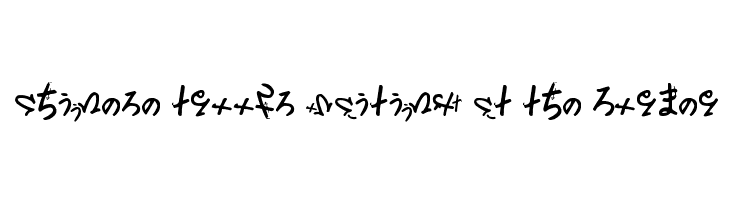
A dynamic and flowing script font with elegant cursive letterforms.
A jagged, hand-drawn font with a gothic, artistic style.
A modern, geometric sans-serif font with clean lines and a technical look.
A bold, decorative font with a 3D effect and dotted textures.
A bold, playful font with rounded strokes and a whimsical style.
A modern, decorative font with elegant uppercase and script-like lowercase letters.
A playful, hand-drawn font with a whimsical and informal style.
A bold, decorative font with wing-like extensions and a gothic flair.
A bold, playful font with a chunky, hand-drawn style.
A bold, modern font with a unique striped pattern for dynamic visual impact.
A bold, distressed font with a rustic, hand-crafted appearance.
A decorative script font with elegant, flowing letterforms and intricate swashes.
A decorative font with characters enclosed in intricate triangular designs.
A thin, modern font for Cherokee script with uniform strokes.
A modern, light, italic sans-serif font with a sleek and slightly condensed design.
A dynamic and fluid script font with elegant, flowing lines.
A lively, expressive handwritten font with fluid, connected strokes.
A dynamic and elegant script font with fluid, connected characters.
An elegant and playful script font with bold, expressive characters.
A bold, brush-style font with dynamic, expressive strokes.
A bold, modern font with a geometric and slightly condensed style.
A bold, playful font with a hand-drawn, liquid-like appearance.
A bold, dynamic handwritten font with thick strokes and playful character.
A bold, geometric font with sharp angles and a vintage flair.
A bold, decorative font with intricate details and ornate flair.
A sleek, futuristic italic font with sharp angles and clean lines.
A graceful script font with flowing, cursive strokes and a refined appearance.
A futuristic, geometric font with a distinct horizontal line pattern.
A modern, flowing italic font with sleek curves and consistent stroke width.
A modern, geometric font with rounded edges and a clean, streamlined appearance.
A decorative script font with elegant, flowing characters and bold weight.
A playful, rounded font with a whimsical and dynamic style.
A dotted, italic font ideal for handwriting practice and educational use.
A futuristic, neon-inspired font with a 3D circuit board design.
An ornate blackletter font with bold, decorative elements and a gothic style.